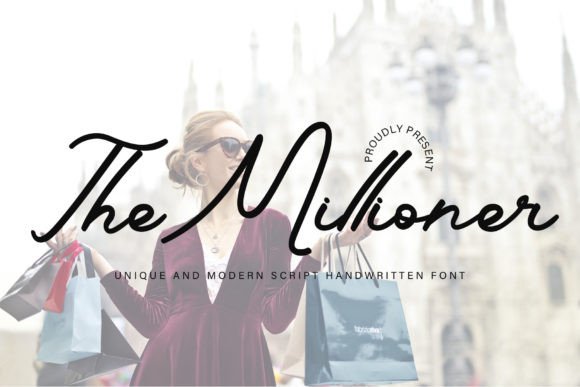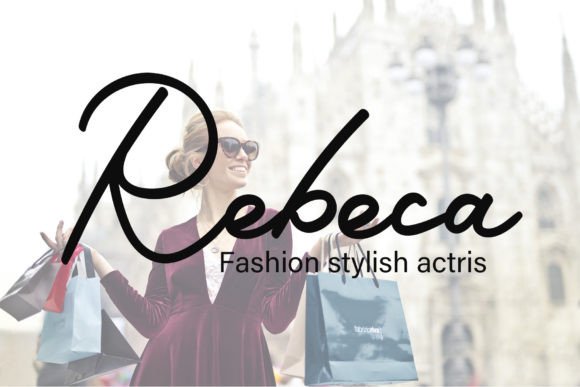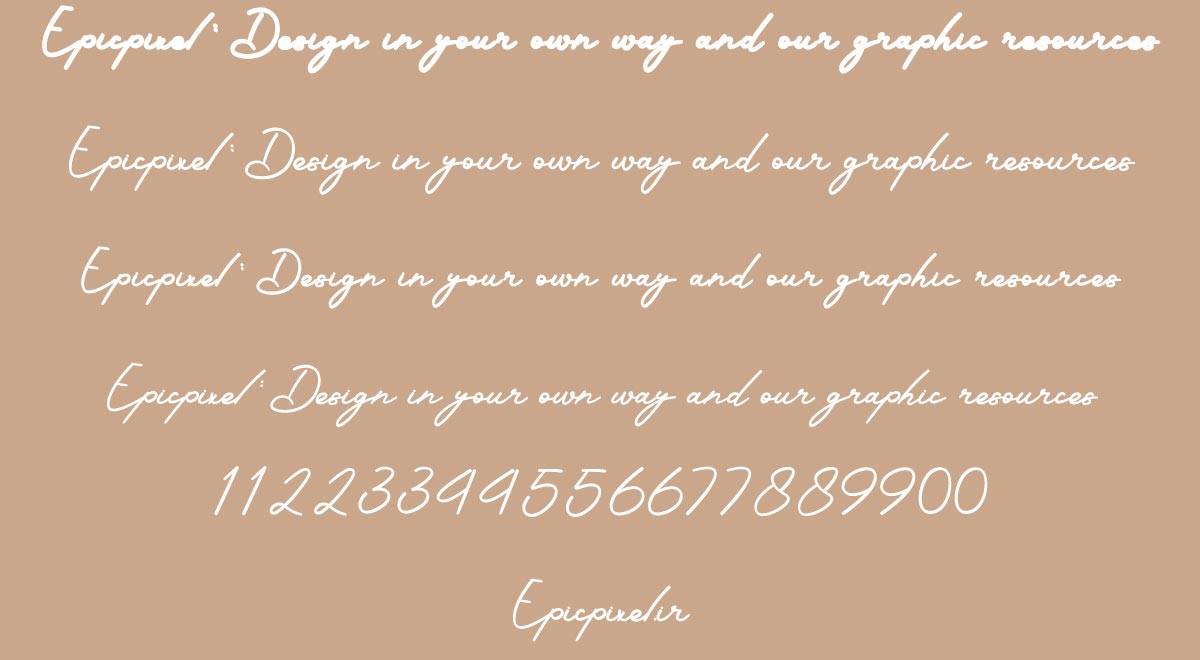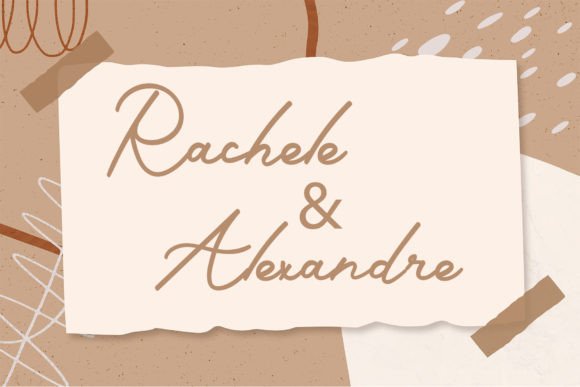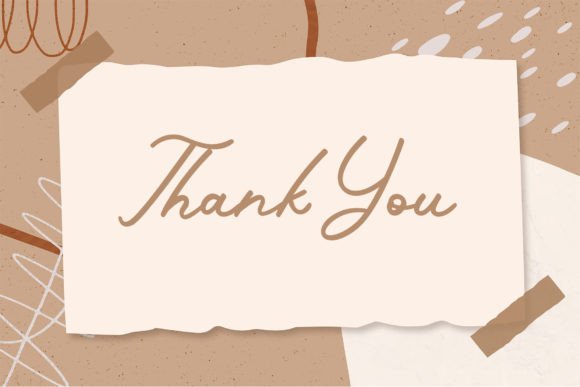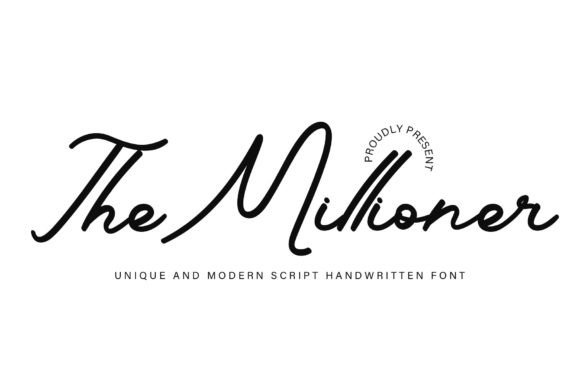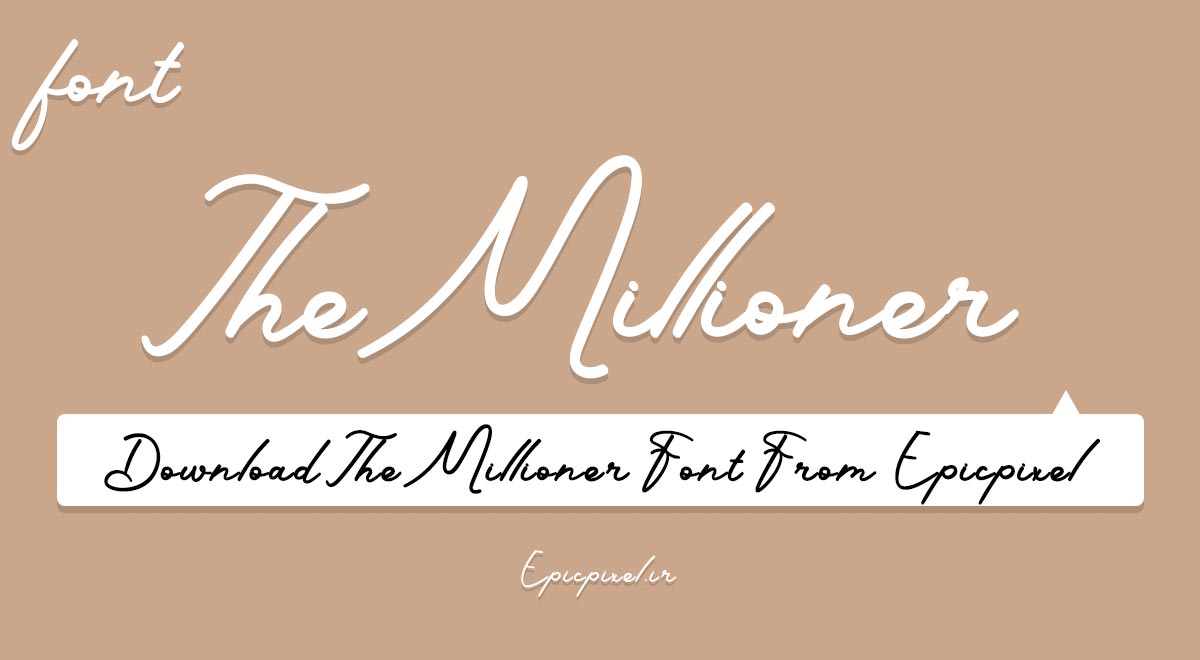
فونت The Millioner انگلیسی
دانلود فونت The Millioner انگلیسی Font د میلیونر |
| ⭐ مجموعه فونت | دانلود فونت انگلیسی میلیونر Font The Millioner |
| ⭐ توضیحات | میلیونر یک فونت دست نویس ساده است. این فونت همه کاره دارای طیف گسترده ای از برنامه های کاربردی از کارت های تبریک گرفته تا سرفصل ها است و تضمین می کند که حس ساده و طبیعی را به پروژه بعدی شما اضافه کند! |